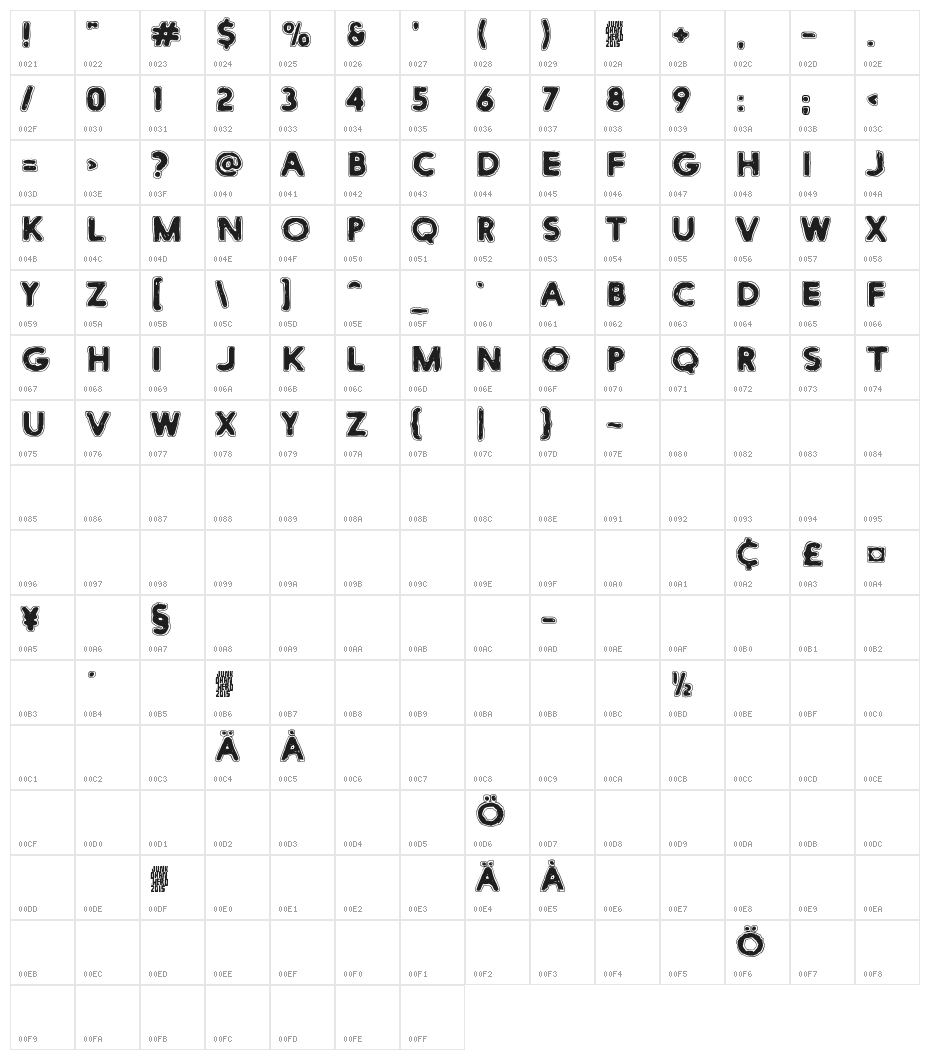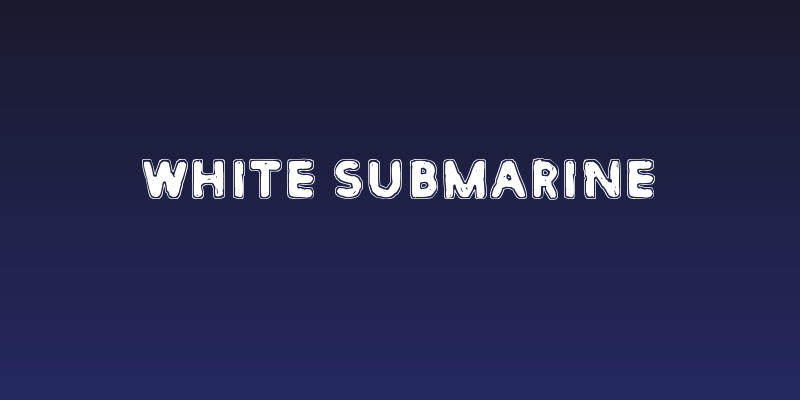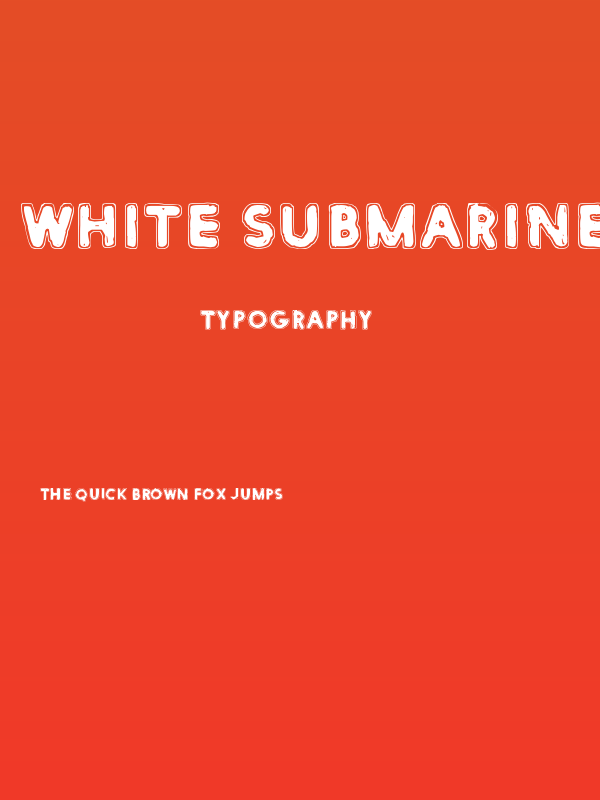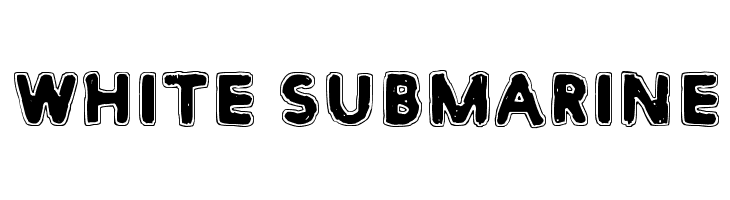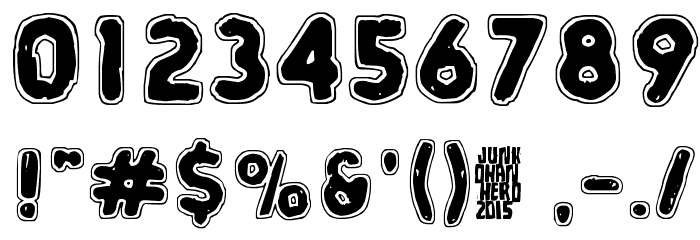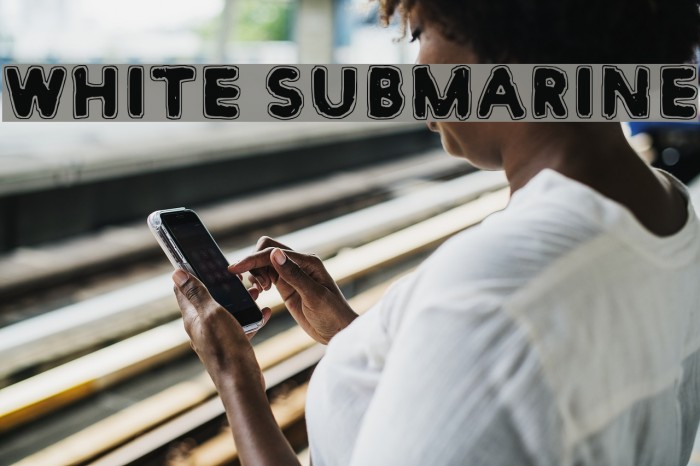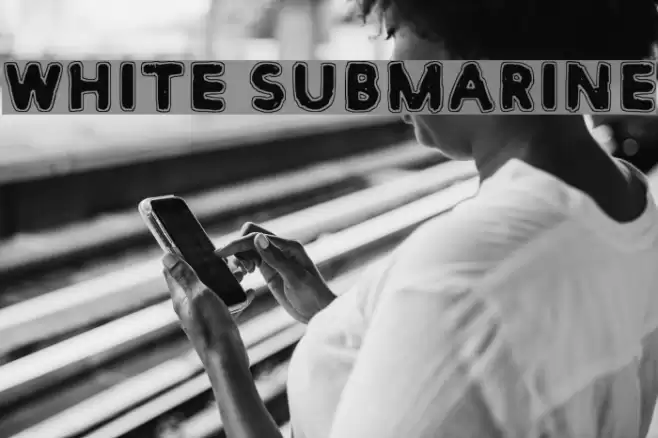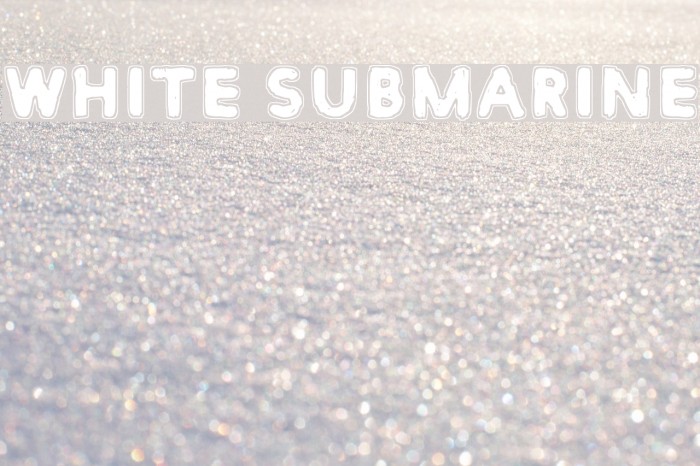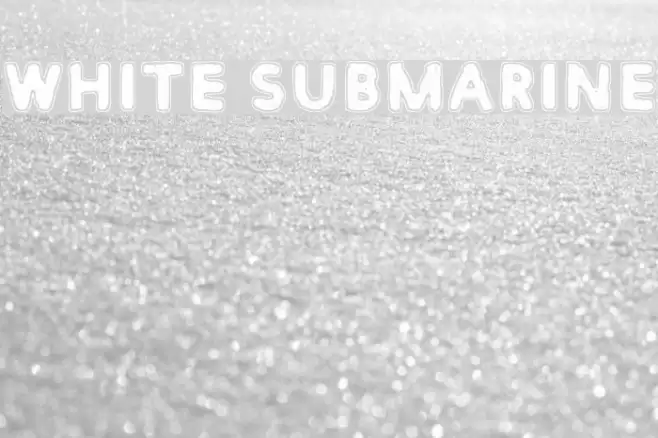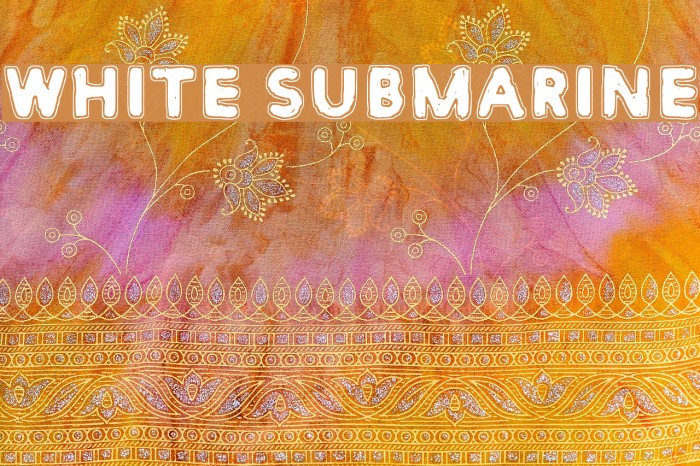
White Submarine Font
✎ Distorted Eroded
| Stil general | Playful, Cartoonish |
| Proiecte propuse | Ideal for children's books, comic strips, playful branding, and casual designs. |